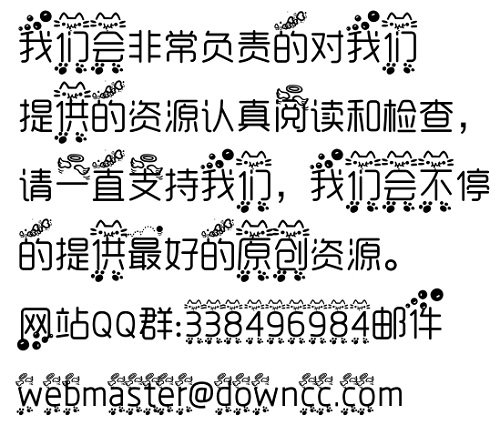
泡泡猫猫字体是一款非常可爱泡泡和猫咪图案的卡通字体,让你的文字更加更加有乐趣和儿童趣味,喜欢的朋友就来绿色资源网体验吧!
泡泡猫猫字体并未将所有的文字变成好看的卡通造型,而是在文字的周围增加了可爱的桃心、棋牌、猫爪印等图案,让文字变得更加温顺乖巧,讨人喜欢。
泡泡猫猫字体兼具艺术字体和pop字体的美感和特色,给人韵味十足的活泼体验,漫画风格的点缀让你的文字更加生动活泼,适用在艺术设计、平面设计等行业。